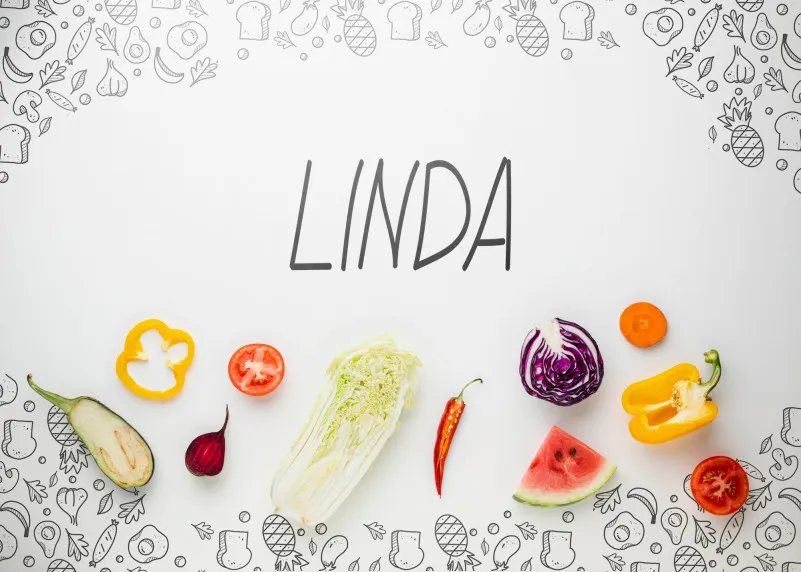
Linda Farmhouse Font
A Linda Farmhouse Font é uma elegante tipografia simples e natural feita à mão, perfeita para quem quer adicionar um toque de simplicidade ao seu design. Esta fonte não se limita a um único tema específico; ela traz vivacidade e naturalidade aos seus trabalhos digitais sem distorcer sua personalidade única. Para designers que buscam uma fonte versátil, ela será definitivamente uma importante adição à coleção de recursos gráficos. É perfeita para criar designs como cartões de aniversário, identidades visuais pessoais ou até mesmo rascunhos do seu próximo livro infantil. Inspirada em um estilo rural e acolhedor da agricultura dos tempos modernos, esta fonte é uma ótima maneira de incorporar o elemento humano na sua arte digital, criando uma conexão única entre os usuários e a mensagem visual. Com certeza ela será um tesouro valioso para qualquer biblioteca de fonts do seu projeto.